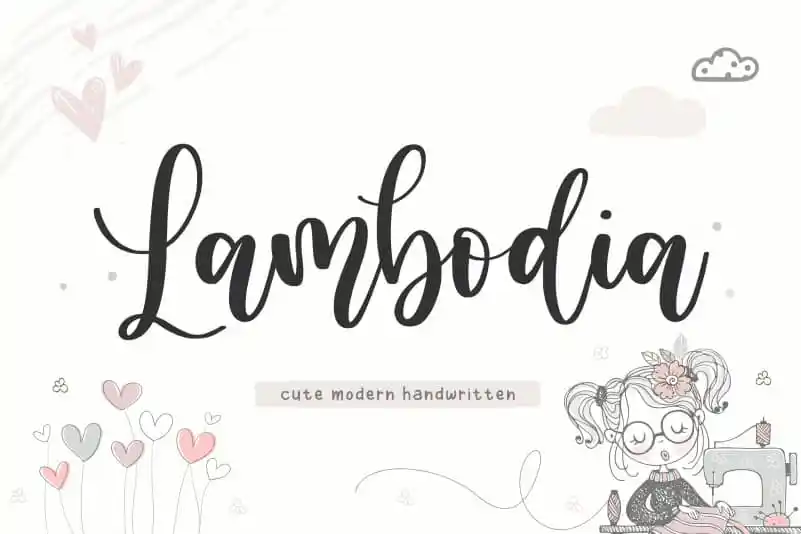
Lambodia Modern Handwritten Font – Download Grátis
A Lambodia Modern Handwritten Font é uma opção perfeita para designers que procuram uma fonte escrita à mão com um toque moderno. Ela se destaca como a escolha ideal para projetos de embalagens, identidade visual e marketing, jornais digitais, mídias sociais, e até mesmo para expressar mensagens em fundos mais elaborados ou simples. Seus traços elegantes e nuances naturais são perfeitamente adaptáveis aos vários usos, tornando-a um recurso valioso tanto para design gráfico quanto para publicidade. Seja você criando embalagens de luxo com sofisticadas cores e imagens icônicas, ou simplesmente querendo comunicar uma mensagem em um projeto social, a Lambodia Modern Handwritten Font está aqui para suportá-lo. Com seu estilo casual mas sempre elegante, esta fonte é perfeita para criar um visual distintivo que destaca seus projetos. É uma opção inovadora para quem deseja agregar um toque único à sua identidade visual ou a qualquer projeto de design gráfico em que possa ser usada.